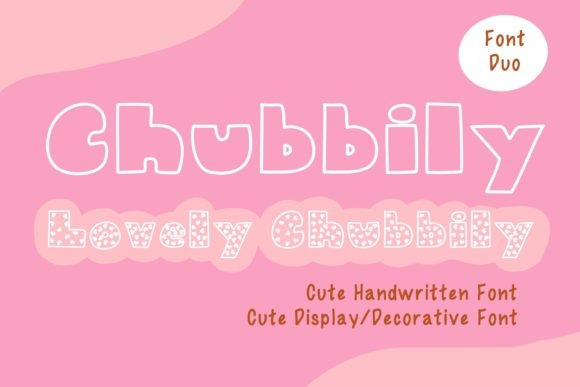
[Creativefabrica] Chubbily and Lovely Chubbily Font (2021)
Название: Chubbily and Lovely Chubbily Font (2021)
Этот совершенно очаровательный дуэт шрифтов (дисплейный и декоративный) может придать веселое настроение любому из ваших прекрасных творений!
Он украсит любой дизайн и создаст модную атмосферу!